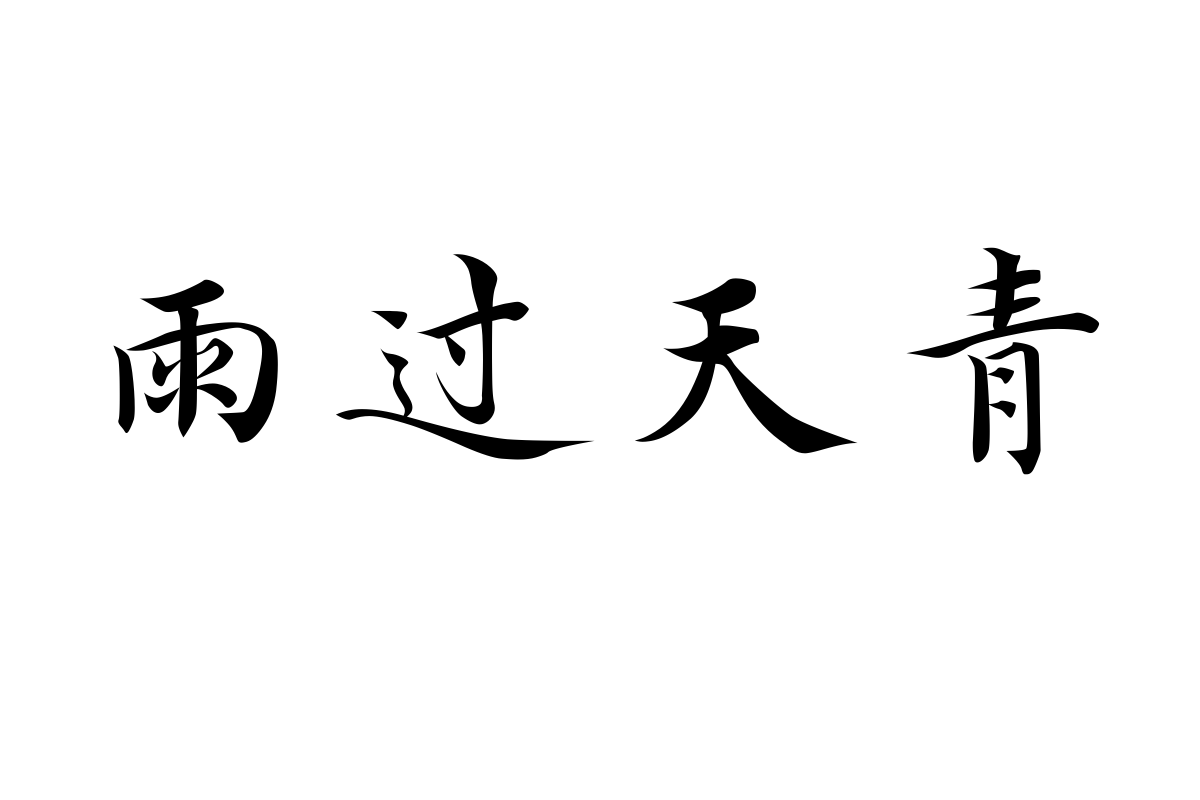
汉仪新蒂馆阁体是一款具有中国传统特色的字体,其特点是字形方正、笔画流畅、结构严谨。这款字体适用于标题、正文、广告、报纸等场合,能够展现出庄重、典雅的氛围。汉仪新蒂馆阁体的笔画粗细适中,既有力度又不失柔美,给人一种稳重而有力的感觉。同时,这款字体的字形结构也较为复杂,需要一定的书法功底才能掌握。总的来说,汉仪新蒂馆阁体是一款非常优秀的中文字体,适合用于各种需要展现传统文化氛围的场合。